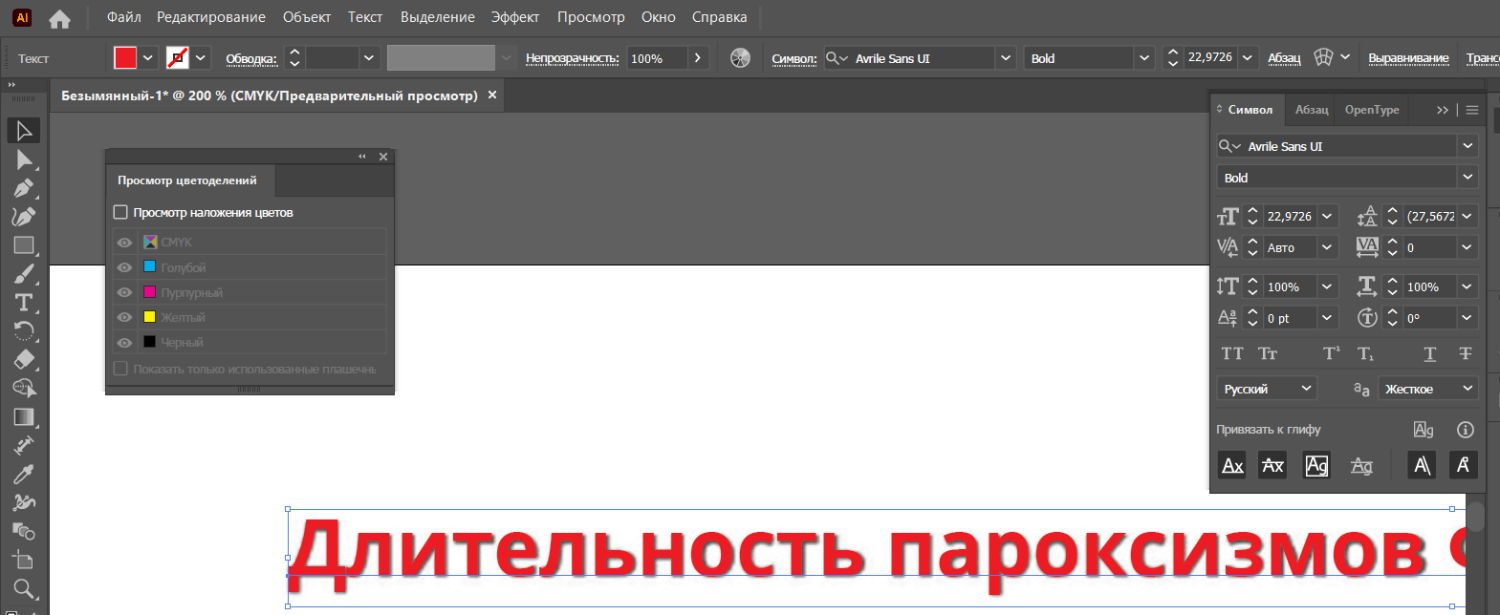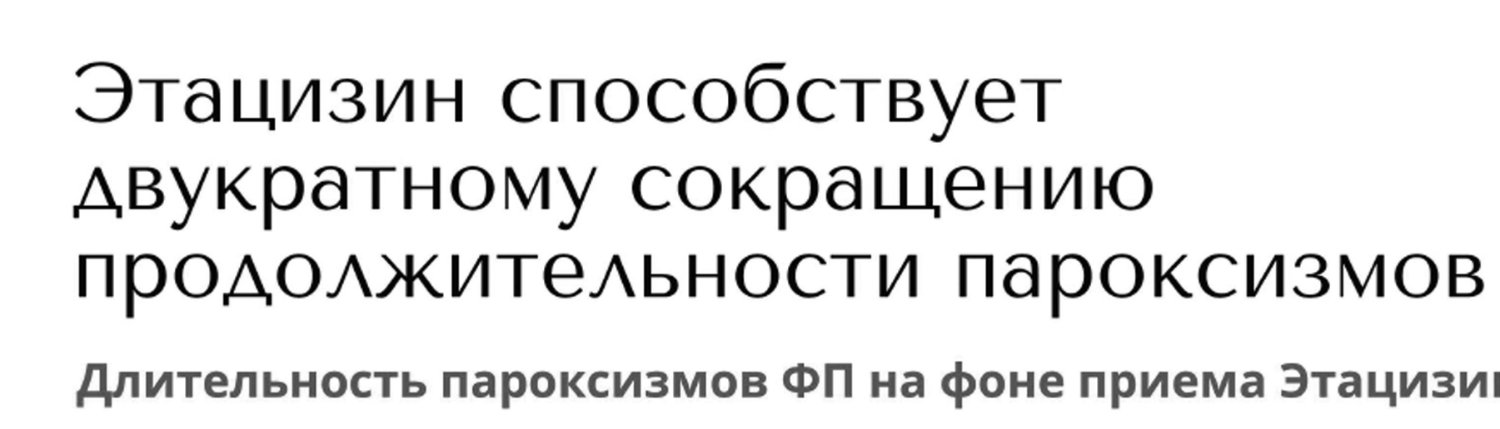
шрифт заголовка и подзаголовка
Добрый вечер, прошу помощи с опознанием. Нужны оба (заголовок + подзаголовок)
Первый Балтика лишенная засечек
подзаголовок
Avrile Sans UI Bold
Второй
у него есть вариант лучше